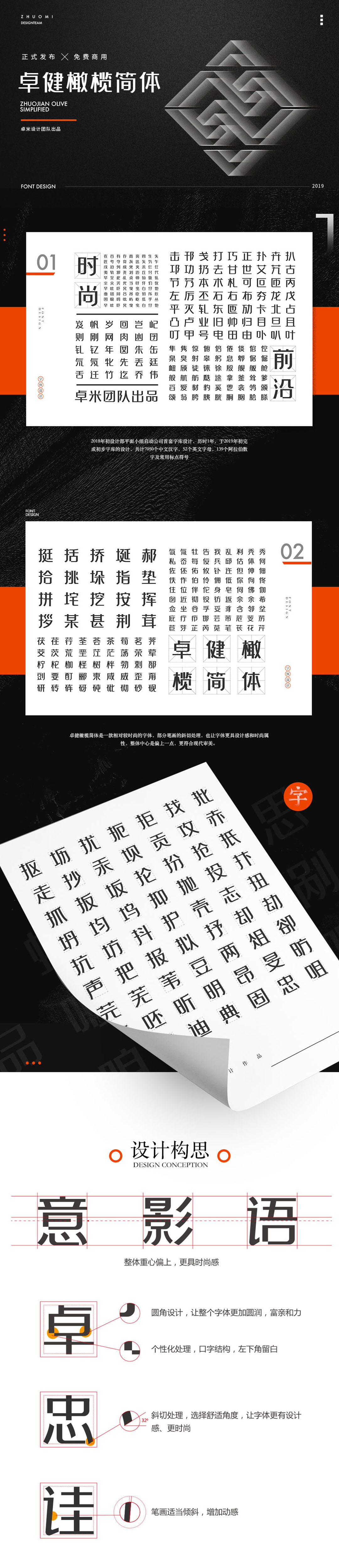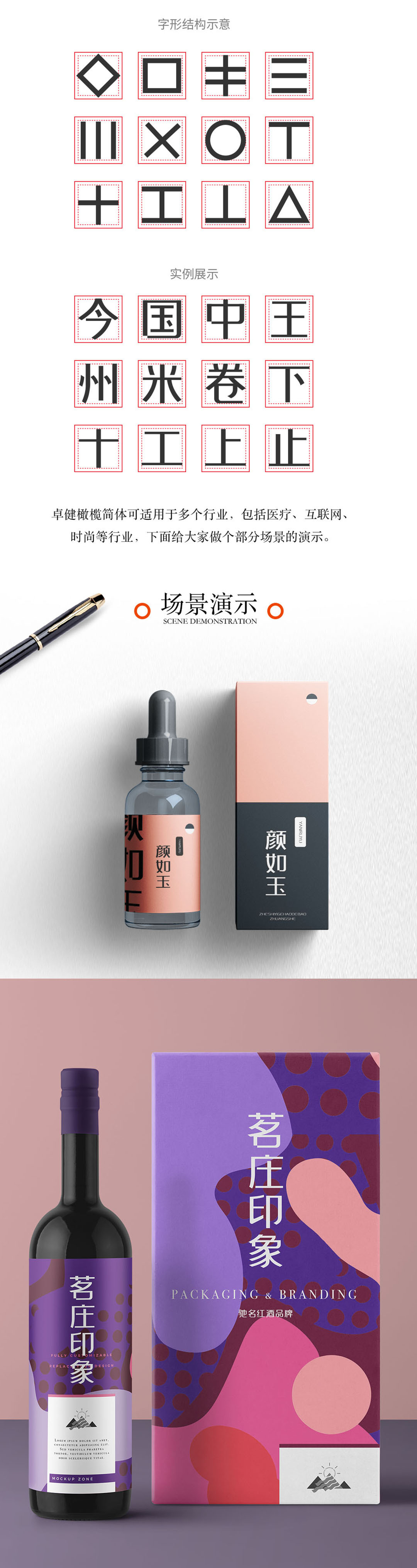
「卓健橄榄简体」是一款相对较时尚的字体,部分笔画的斜切处理,也让字体更具设计感和时尚属性,整体中心是偏上一点,更符合现代审美。字体圆角设计,让整个字体更加圆润,富亲和力。口字结构,左下角留白,个性化处理更具特色。字体斜切32度处理,让字体更有设计感更时尚。「卓健橄榄简体」可适用于多个行业,包括医疗、互联网、时尚等行业。